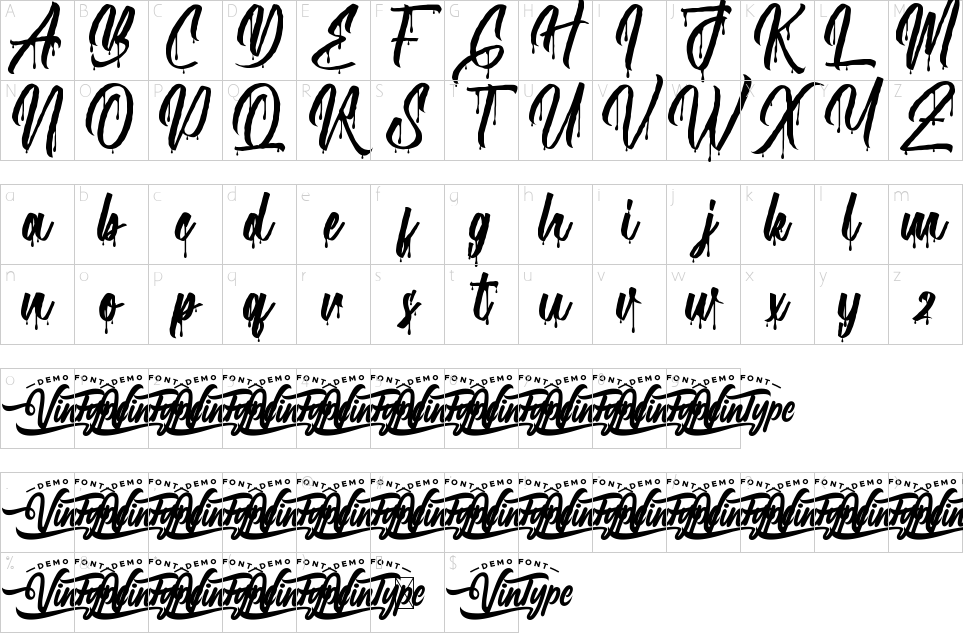
Descubra a essência da luta contínua com Fight Hard Font. Esta elegante e poderosa fonte foi cuidadosamente projetada pelo designer desconhecido vintype, disponível tanto para computadores Windows quanto Mac. Desde sua introdução, o Fight Hard se tornou uma escolha popular entre designers devido à sua qualidade robusta e acentos agressivos que ajudam a destacar qualquer texto usado. Com mais de 6.210 downloads desde seu lançamento, você pode ter certeza de que esta font será um forte aliado em suas próximas criações digitais. Explore a resistência contínua no estilo do Fight Hard Font e transforme a forma como você expressa sua identidade visual.